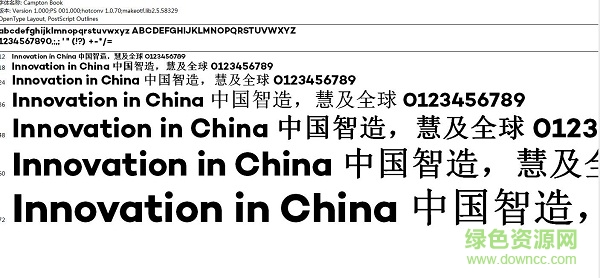
软件介绍 软件标签: campton字体 英文字体 campton字体包括campton bold字体、campton book字体、campton light字体、campton medium以及campton bolddemo等无衬线字体,字型饱满,布白得当,非常实用,欢迎大家免费下载!字体排版术语介绍【字号】区分活字大小的称谓【横排】字符横向顺序排列成行的排版格式。【竖排】 字符由上而下竖向排列成行的排版格式。【印刷字体】供排版印刷用的规范化文字形体。campton字体安装方法方法一:控制面板/字体/文件/安装新字体;方法二:直接将字体复制到C:\WINDOWS\Fonts。方法三:针对win7系统,用户只需选中字体右键安装即可。 软件截图 上一张下一张(1 / 1) 安装详细截图 其他版本下载 标题 大小 更新日期 下载 下载地址 电脑版 campton light/book/bold字体 点击报错 软件无法下载或下载后无法使用,请点击报错,谢谢! 关闭报错反馈 请描述您所遇到的错误,我们将尽快予以修正,谢谢! *必填项,请输入内容 本类最新 sounso beauty字体 spyced哥特英文字体 ttf版 zerodegrees字体 the next font ttf版 coolvetica font keep calm ttf 免费版 相关文章 开机时报错:" Error: System security- The system has been tempered with press F1 to enter Setup" photoshop常用快捷键指南 Apache 的 httpd.conf 详解(很实用) 关闭xp防火墙加速bittorrent下载 Samba中解决手动F5刷新文件列表 .Net基础:ASP.NET中的session存储模式运用 用户评论 热门评论 最新评论 发表评论 查看所有评论(0) 昵称: 请不要评论无意义或脏话,我们所有评论会有人工审核. 字数: 0/500 (您的评论需要经过审核才能显示)